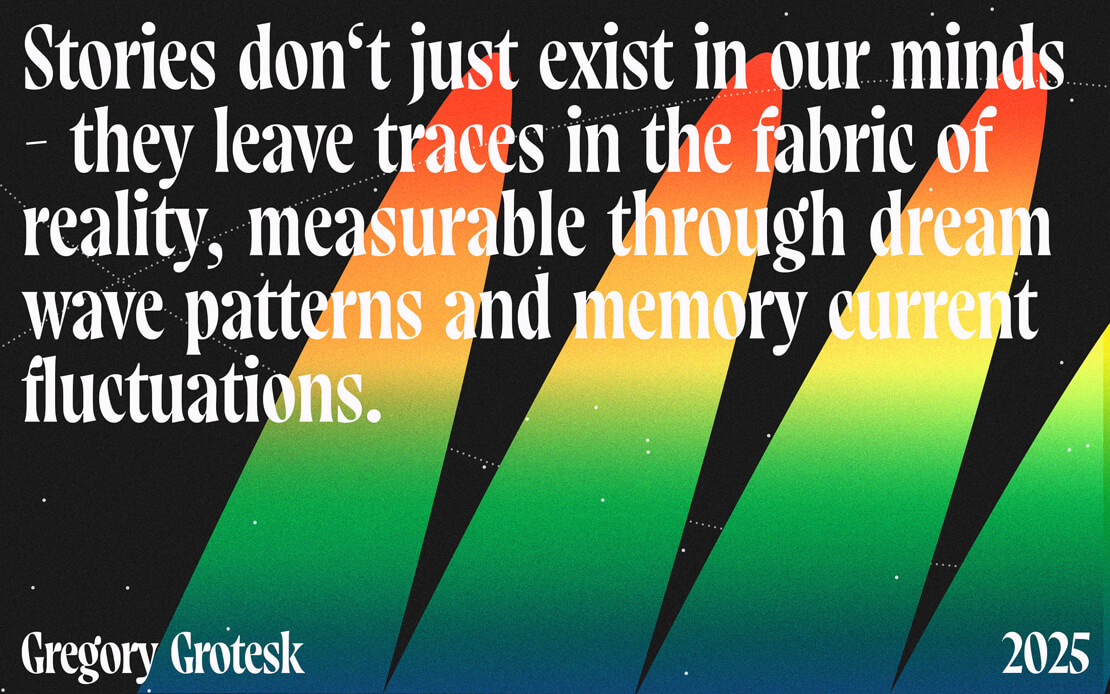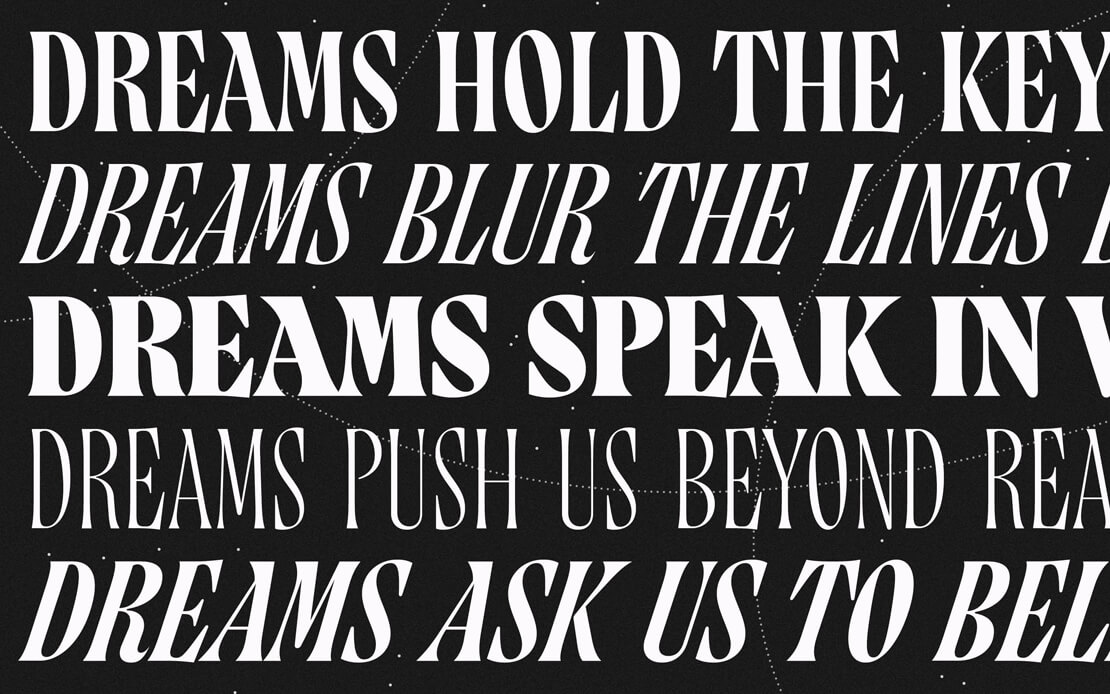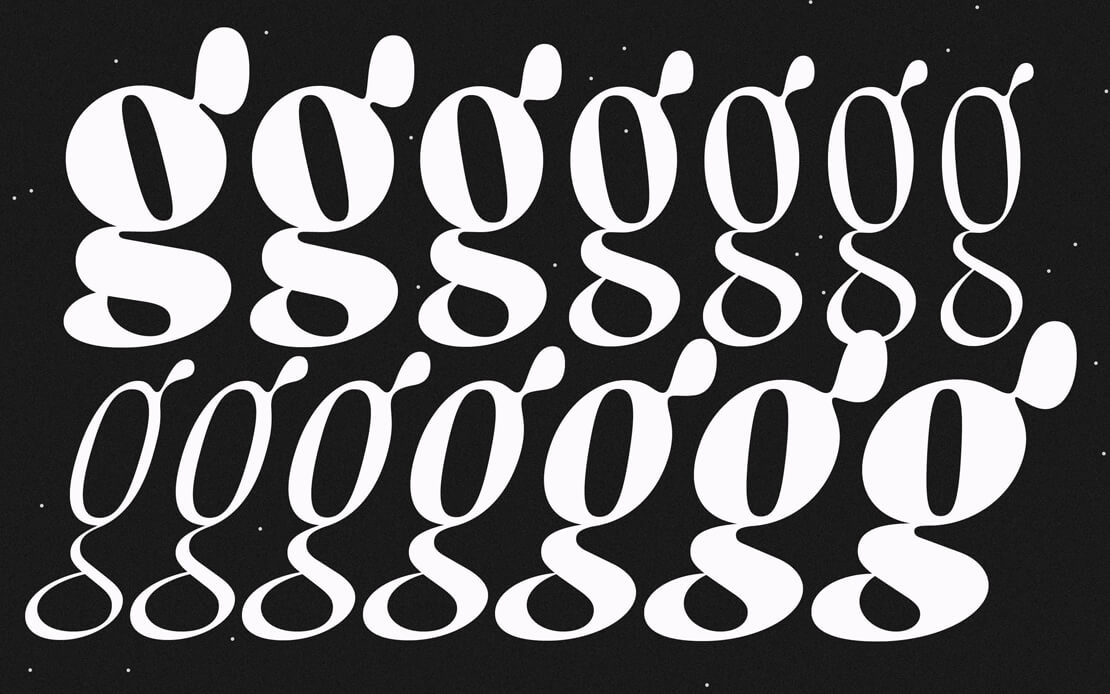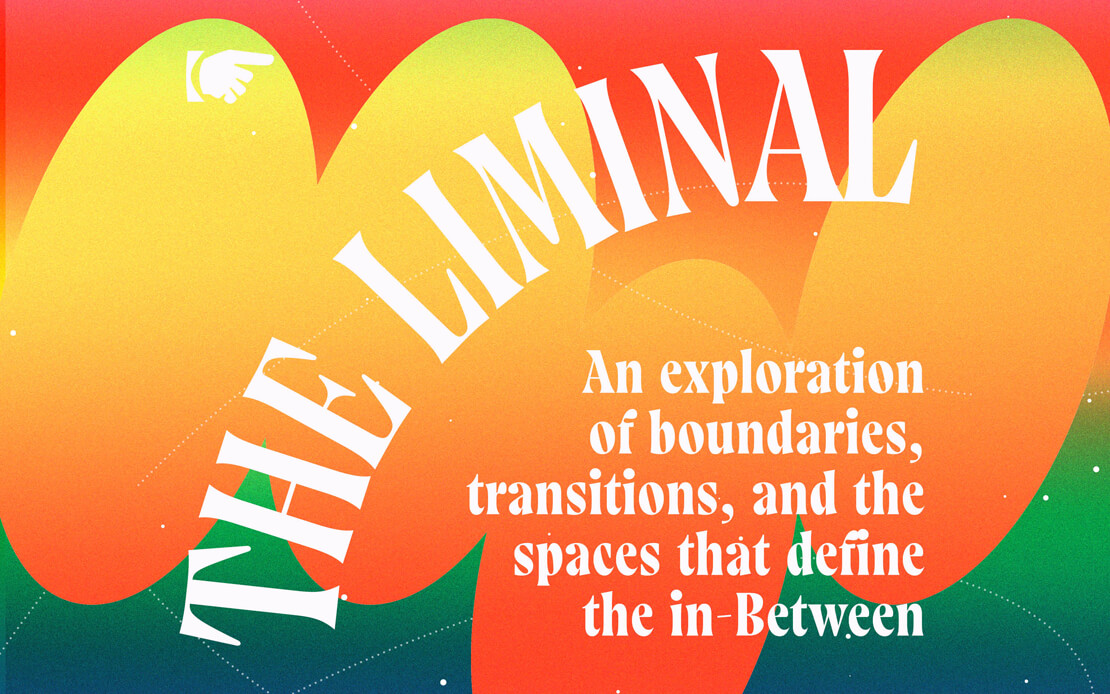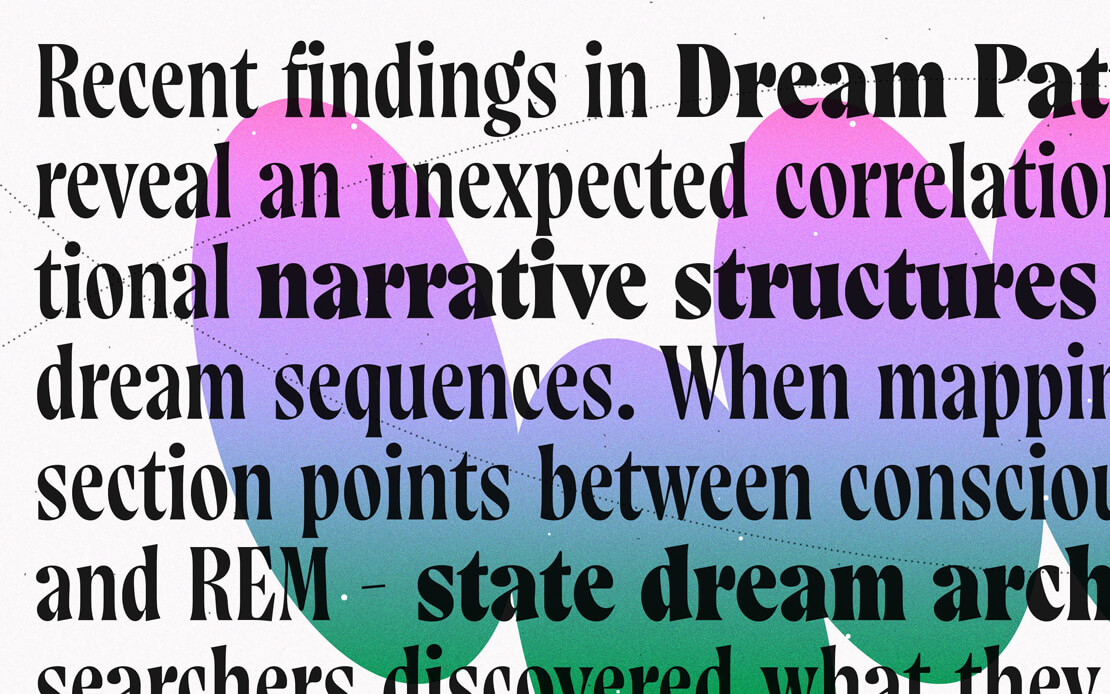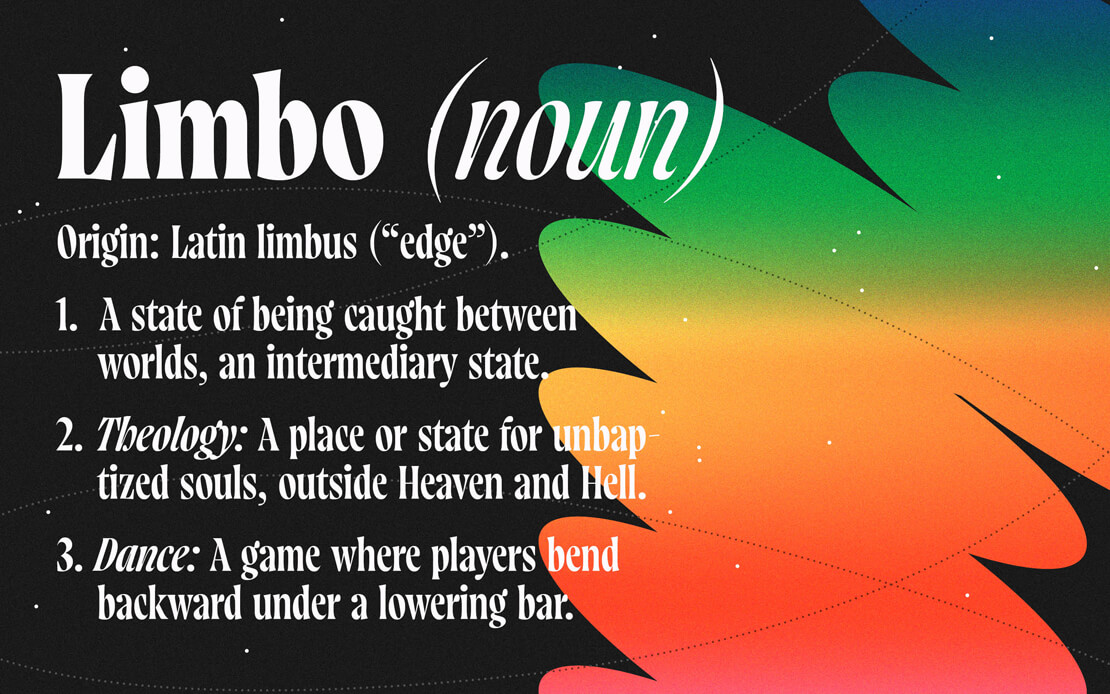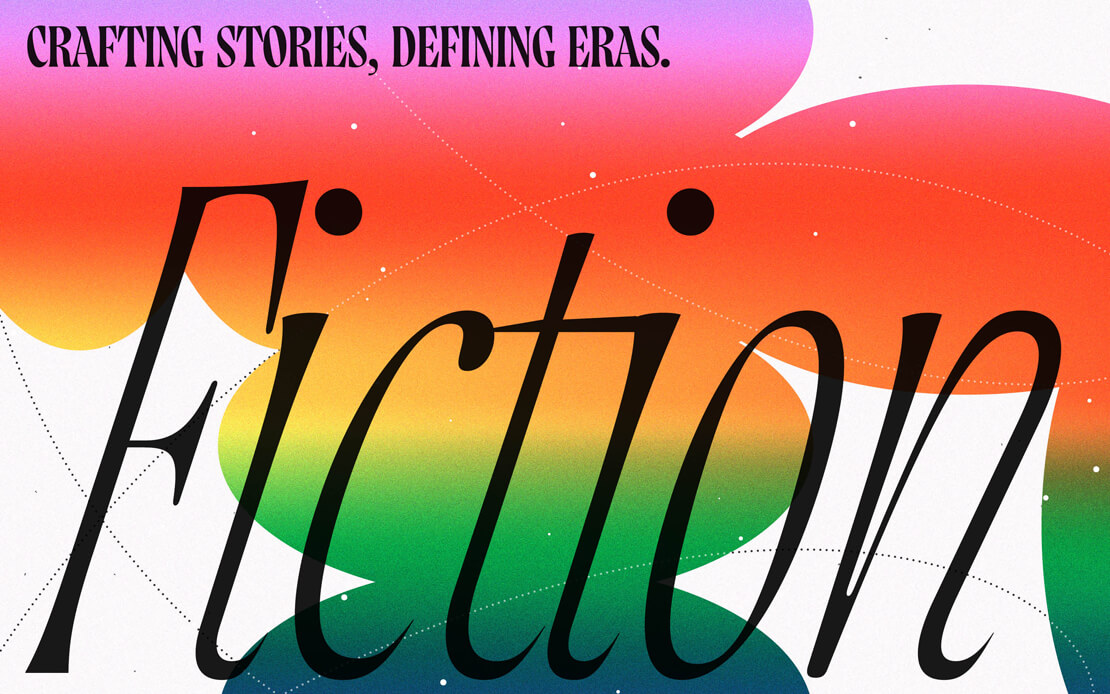
Exzentrische Schriftfamilie »Gregory Poster« bei TypeMates erschienen
Mit »Gregory Poster« veröffentlicht TypeMates eine exzentrische Schriftfamilie, die eine Ode an analoge Druckproduktion darstellt. Lebendige Unregelmäßigkeiten schaffen Charakter und sollen wohlig warme Erinnerungen an eine frühere Zeit wecken.
Gregory Poster versteht sich als zeitgenössische Interpretation analoger Ästhetik. Statt auf geometrische Perfektion zu setzen, greift die Schrift bewusst zu überzeichneten Details und lebendigen Unregelmäßigkeiten.
Horizontale Stammserifen sind sanft gekehlt, die Schattenachse ist deutlich geneigt, der Kontrast in den Strichstärken prägnant ausgeführt. In Kombination mit einer kopflastigen Konstruktion entsteht ein Erscheinungsbild, das bewusst an typografische Elemente und das Flair vergangener Jahrzehnte erinnern soll.
Die Schnitte reichen von »Thin« bis »xBold«. Darüber hinaus steht auch ein Variable Font zur Verfügung. Die entsprechenden Kursiven greift den expressiven Charakter weiter auf und verleiht Texten durch ihren ausgeprägten Neigungswinkel zusätzliche Dynamik.
Gregory Poster unterstützt über 270 Sprachen, darunter Griechisch, Kyrillisch und Vietnamesisch. Neben mehreren Ziffernsätzen stehen auch OpenType-Features, sprachspezifische Varianten sowie ausgewählte Symbole und Emojis zur Verfügung.
Gestaltet wurde die Schrift von Jakob Runge in Zusammenarbeit mit George Triantafyllakos und Seryozha Rasskazov.